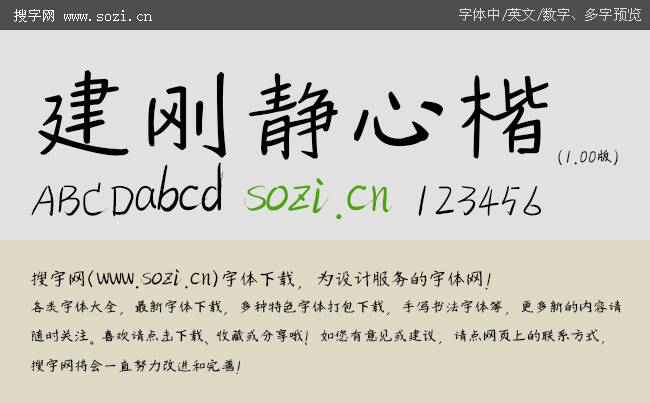
建剛靜心楷
搜字網(wǎng)提供一款建剛靜心楷中文書(shū)法字體下載,建剛靜心楷是一款手寫(xiě)風(fēng)格的楷體書(shū)法字體,字體端正,字形大方,整體效果十分出色,適合應(yīng)用于廣告設(shè)計(jì)、名片設(shè)計(jì)、包裝印刷、兒童產(chǎn)品設(shè)計(jì)等應(yīng)用。